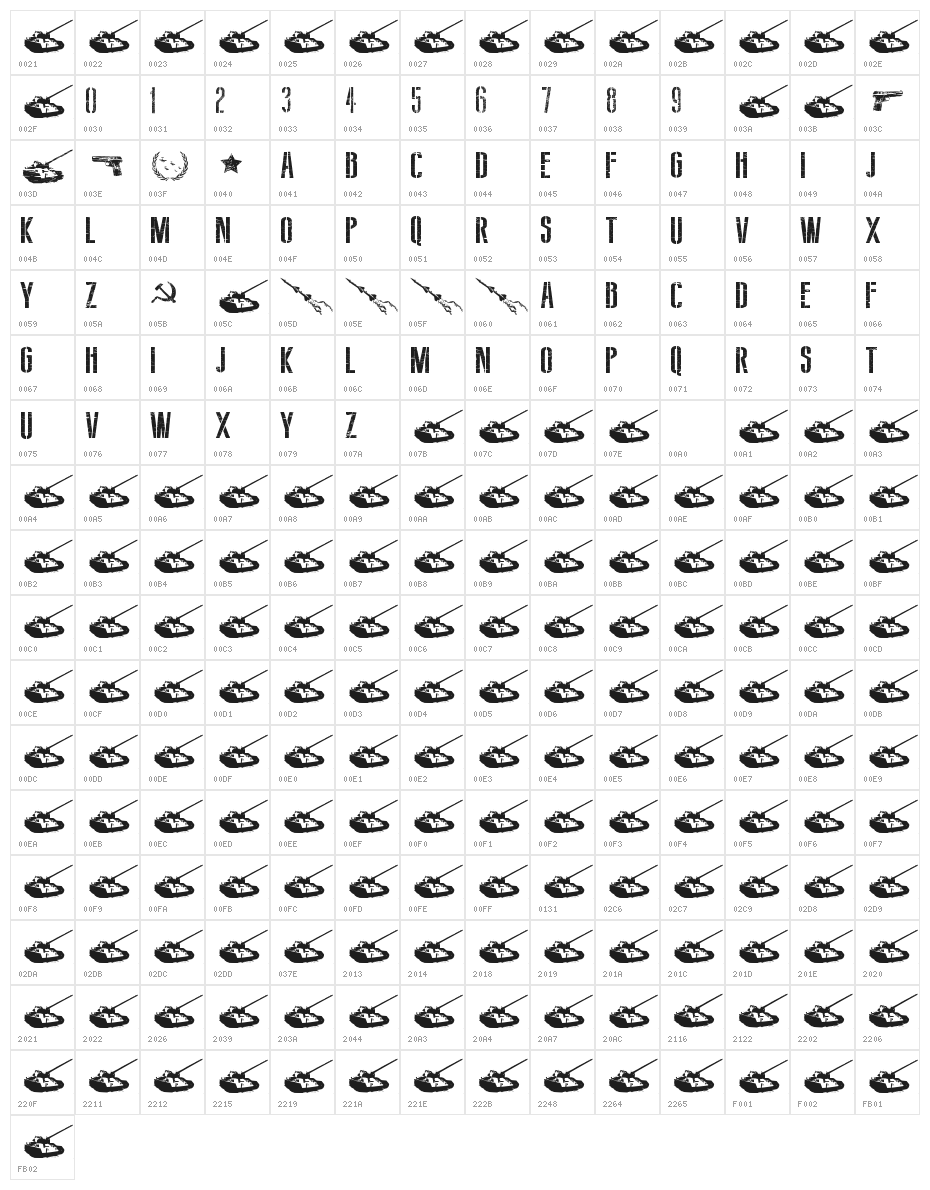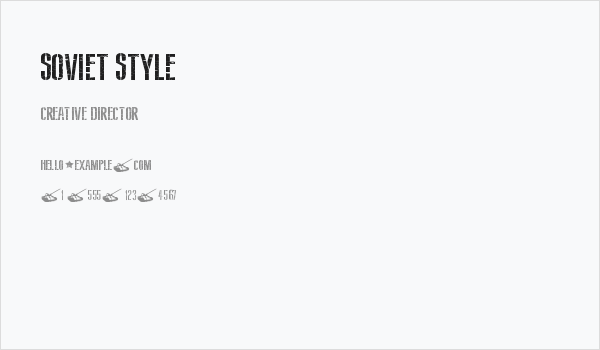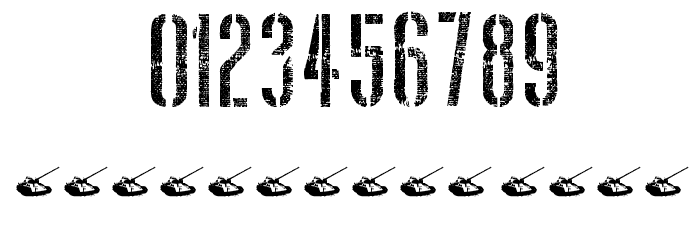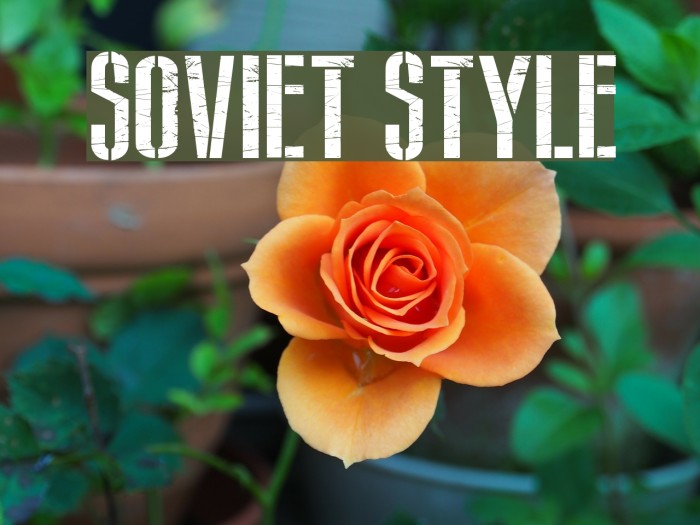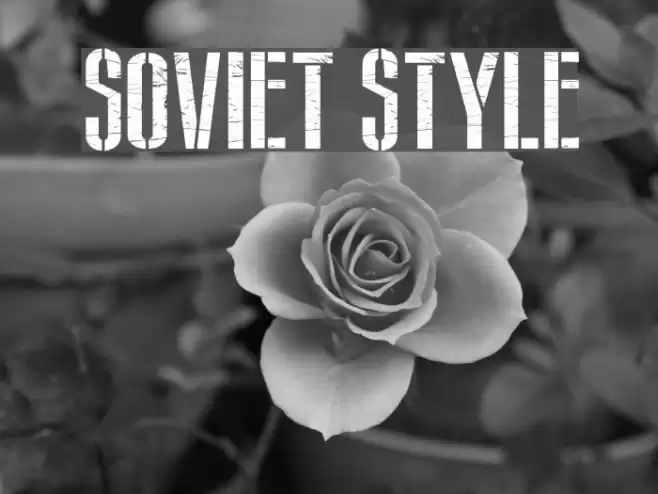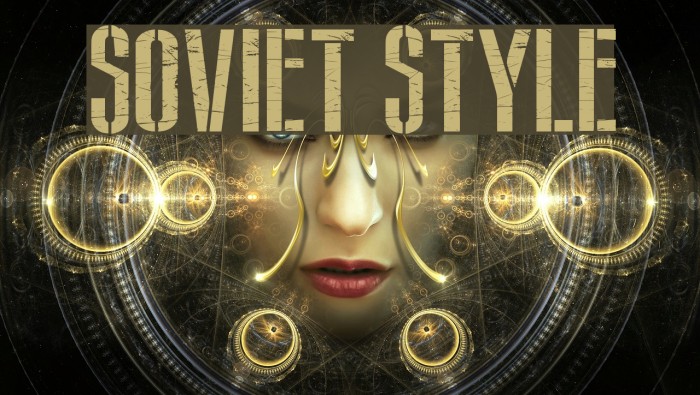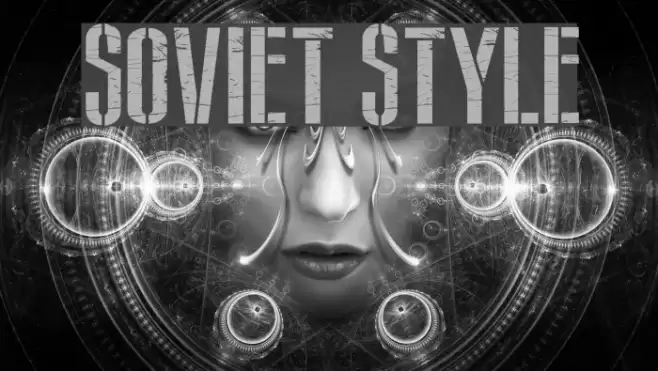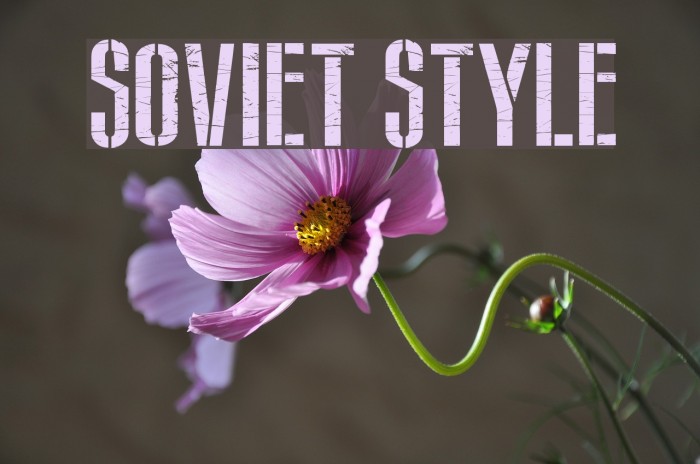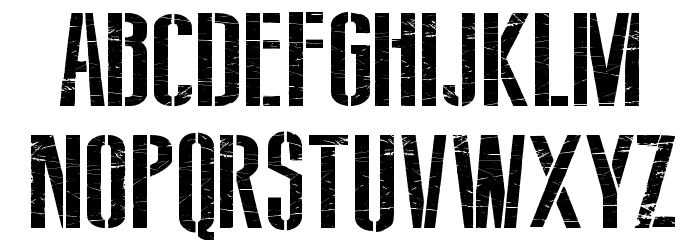
Soviet Style Font
✎ Stencil
| Категория | Stencil |
| Общий стиль | Vintage |
| Рекомендуемые проекты | Ideal for projects requiring a vintage or industrial theme, such as posters, banners, or branding for products with a rugged or historical appeal. |